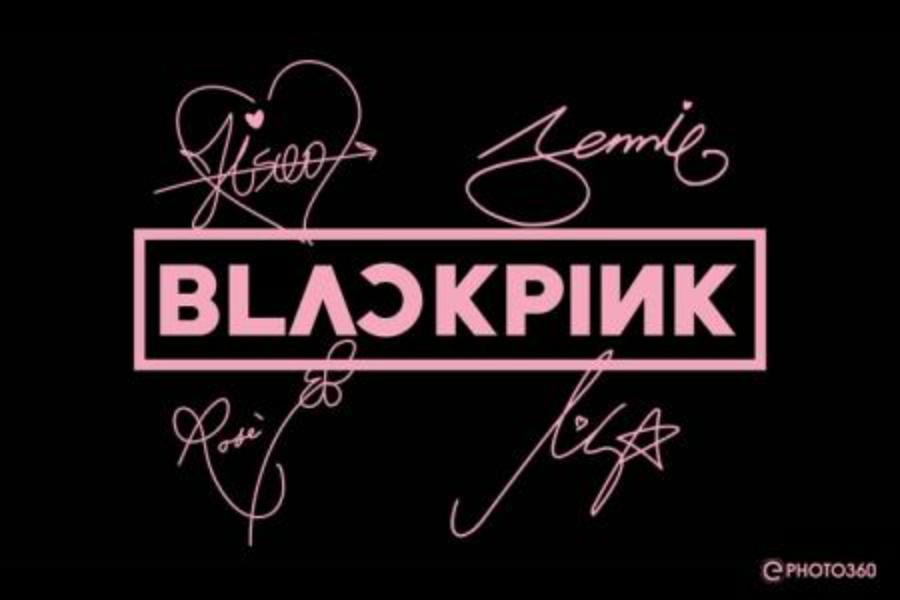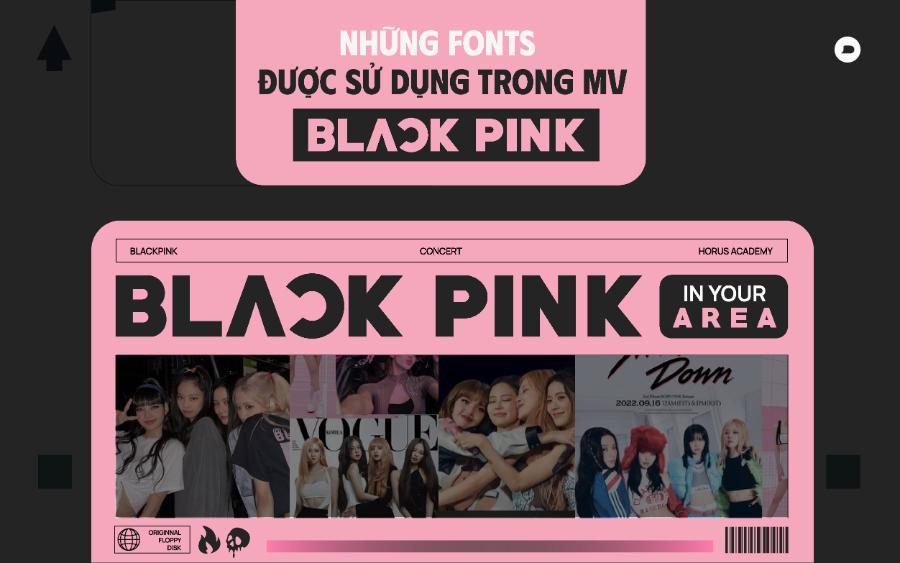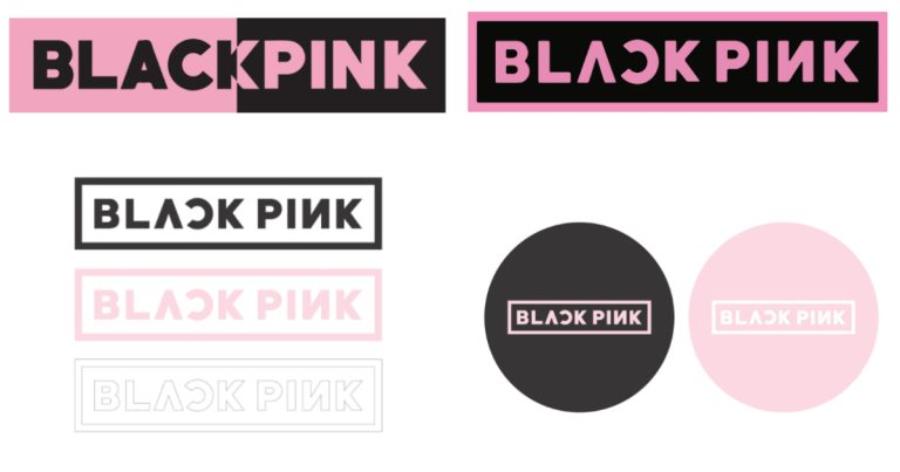
Khám Phá Các Font Chữ Độc Đáo Tạo Nên Thương Hiệu BLACKPINK
Tìm hiểu về các font chữ BLACKPINK đang sử dụng trong các chiến dịch quảng bá và hình ảnh thương hiệu. Khám phá những yếu tố tạo nên sự nổi bật trong thiết kế của nhóm nhạc K-pop đình đám này.
Khám Phá Các Font Chữ Độc Đáo Tạo Nên Thương Hiệu BLACKPINK
BLACKPINK, nhóm nhạc K-pop đình đám, không chỉ nổi tiếng với âm nhạc tuyệt vời mà còn với phong cách thời trang và hình ảnh thương hiệu đặc trưng. Một phần trong sự thành công của BLACKPINK chính là cách họ sử dụng các font chữ trong các chiến dịch quảng bá, album, và hình ảnh thương hiệu. Trong bài viết này, sadesign sẽ cùng bạn khám phá các font chữ BLACKPINK đang sử dụng và tại sao chúng lại tạo nên dấu ấn riêng biệt của nhóm.
1.Giới thiệu về BLACKPINK và sự quan trọng của font chữ trong thương hiệu
BLACKPINK, nhóm nhạc K-pop quốc tế nổi tiếng, không chỉ gây ấn tượng với những bản hit đình đám mà còn sở hữu một hình ảnh thương hiệu sắc nét và độc đáo. Phong cách của nhóm được thể hiện rõ nét không chỉ qua âm nhạc mà còn qua các yếu tố hình ảnh, bao gồm logo, màu sắc, và đặc biệt là font chữ. Font chữ, mặc dù có vẻ là một yếu tố nhỏ trong tổng thể chiến lược thương hiệu, nhưng lại đóng vai trò quan trọng trong việc tạo dựng bản sắc và nâng cao sự nhận diện của BLACKPINK trên toàn cầu.
Trong việc xây dựng thương hiệu, font chữ đóng vai trò quan trọng trong việc truyền tải thông điệp và bản sắc của nhóm. Font chữ không chỉ là yếu tố thẩm mỹ mà còn tạo nên sự nhận diện đặc trưng, giúp khán giả dễ dàng liên kết với hình ảnh của BLACKPINK. Sự lựa chọn cẩn thận về kiểu dáng, kích thước và màu sắc font chữ góp phần củng cố giá trị thương hiệu, tạo cảm giác chuyên nghiệp và thu hút sự chú ý trong mọi sản phẩm truyền thông của nhóm. Điều này cho thấy tầm quan trọng của việc chú trọng đến từng chi tiết nhỏ trong việc xây dựng hình ảnh thương hiệu toàn diện.
2. BLACKPINK và chiến lược thương hiệu
Thương hiệu của BLACKPINK đã được xây dựng một cách tinh tế, từ âm nhạc đến hình ảnh, tất cả đều phối hợp nhịp nhàng để tạo nên một tổng thể hoàn hảo. Các thành viên của nhóm đều có cá tính riêng biệt, nhưng khi kết hợp lại, họ tạo thành một nhóm thống nhất với một phong cách chung đặc trưng. Chính điều này cũng được thể hiện rõ qua cách mà BLACKPINK sử dụng các font chữ trong các sản phẩm âm nhạc, poster, quảng cáo, và nhiều hơn nữa.
Một trong những yếu tố quan trọng trong việc tạo dựng thương hiệu cho BLACKPINK chính là việc lựa chọn các font chữ. Font chữ không chỉ đơn giản là kiểu dáng chữ mà chúng còn truyền tải thông điệp, cảm xúc và sự cá tính của nhóm. Vì vậy, việc lựa chọn font chữ của BLACKPINK không chỉ dựa trên thẩm mỹ mà còn phải phù hợp với thông điệp mà nhóm muốn truyền tải.
3. Những font chữ chính BLACKPINK sử dụng
Font chữ đóng vai trò quan trọng trong việc truyền tải thông điệp và tạo dựng hình ảnh thương hiệu. BLACKPINK đã rất khéo léo lựa chọn những font chữ phù hợp với từng sản phẩm, từ logo, album, poster đến các ấn phẩm truyền thông khác. Việc phân tích và tìm hiểu về các font chữ này không chỉ giúp người hâm mộ hiểu rõ hơn về phong cách thiết kế của nhóm mà còn mang đến những kiến thức hữu ích cho những ai quan tâm đến lĩnh vực thiết kế đồ họa.
3.1. Font chữ BLACKPINK Logo
Logo và tên nhóm BLACKPINK thường được thiết kế với một font chữ đặc biệt, mang đậm dấu ấn riêng và thể hiện cá tính của nhóm. Font chữ này thường là sự kết hợp giữa nét hiện đại và nét cổ điển, tạo nên một tổng thể hài hòa và độc đáo. Tuy nhiên, tên chính xác của font chữ này vẫn chưa được công bố rộng rãi.
Logo của BLACKPINK là một biểu tượng đặc trưng của nhóm, và font chữ trong logo này rất dễ nhận ra. Tên BLACKPINK được viết bằng font chữ sans-serif, sắc nét và mạnh mẽ. Font chữ này mang lại cảm giác hiện đại, trẻ trung nhưng cũng rất sang trọng, phù hợp với hình ảnh của một nhóm nhạc quốc tế.
Đặc điểm nổi bật của font chữ trong logo BLACKPINK là đường nét thẳng và dứt khoát, thể hiện sự quyết đoán và năng lượng mạnh mẽ của nhóm. Sự kết hợp giữa độ đậm và khoảng cách giữa các chữ cái tạo nên một cảm giác cân đối, mạnh mẽ nhưng không quá cứng nhắc. Điều này giúp BLACKPINK thể hiện được sự tự tin và cá tính đặc biệt của mình.
3.2. Font chữ cho các album và sản phẩm âm nhạc
BLACKPINK luôn chú trọng đến việc lựa chọn font chữ cho các album của mình. Mỗi album thường có một hoặc nhiều font chữ khác nhau, thể hiện chủ đề và phong cách riêng. Ví dụ, trong album "Square Up", nhóm đã sử dụng font chữ Exocet cho phần tiêu đề, tạo nên vẻ mạnh mẽ và cá tính.
Ngoài logo, BLACKPINK còn sử dụng các font chữ khác nhau trong các sản phẩm âm nhạc của mình. Trong các album, single và các hình ảnh quảng bá, BLACKPINK sử dụng những font chữ hiện đại, dễ đọc nhưng cũng rất phong cách. Các font chữ này thường có sự kết hợp giữa phong cách cổ điển và hiện đại, vừa mang tính đương đại vừa gợi nhớ đến những yếu tố hoài cổ.
Một ví dụ điển hình là trong album "The Album," nhóm sử dụng một font chữ sans-serif tinh tế, dễ dàng làm nổi bật tên album và các bài hát. Sự kết hợp giữa chữ in hoa và in thường khiến thiết kế trở nên thú vị và dễ dàng thu hút sự chú ý của người xem.
5. Kết luận
BLACKPINK không chỉ là một nhóm nhạc với tài năng âm nhạc tuyệt vời mà còn là một biểu tượng của thời trang và phong cách. Việc sử dụng các font chữ một cách chiến lược đã góp phần tạo nên hình ảnh thương hiệu mạnh mẽ và dễ nhận diện của nhóm. Font chữ không chỉ là công cụ truyền tải thông điệp, mà còn là một phần quan trọng trong việc xây dựng một BLACKPINK có phong cách riêng biệt và ấn tượng trên toàn thế giới.